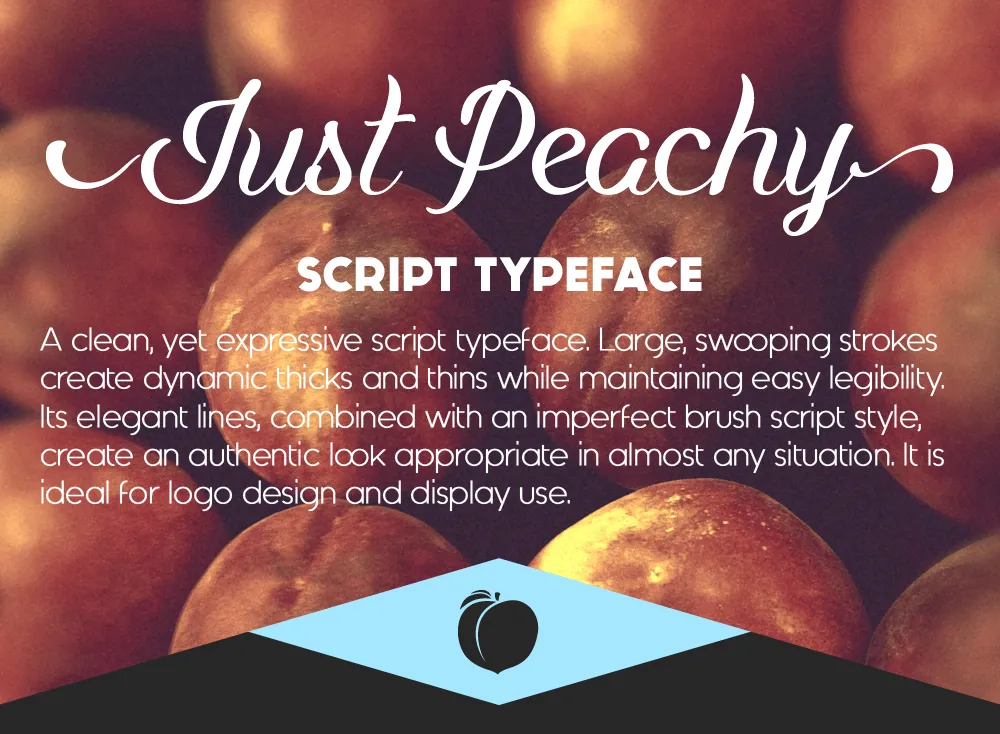
A fonte Just Peachy Script é um script elegante e expressivo criado por Hamilton. Com traços grandes e fluidos que criam contrastes dinâmicos entre os espaçamentos, ela mantém uma leitura clara e fácil. As linhas delicadas, combinadas com o estilo de tinta feita a mão imperfeita, produzem um visual autêntico adequado para qualquer situação. É especialmente ideal para uso em logomarcas e aplicações visuais chamativas. Ideal para quem busca uma fonte que combine elegância com um toque irretocável. Just Peachy Script é perfeita para personalizar seus projetos de forma única e moderna.